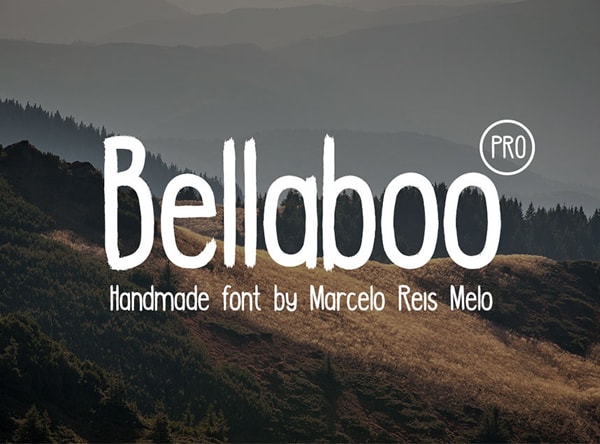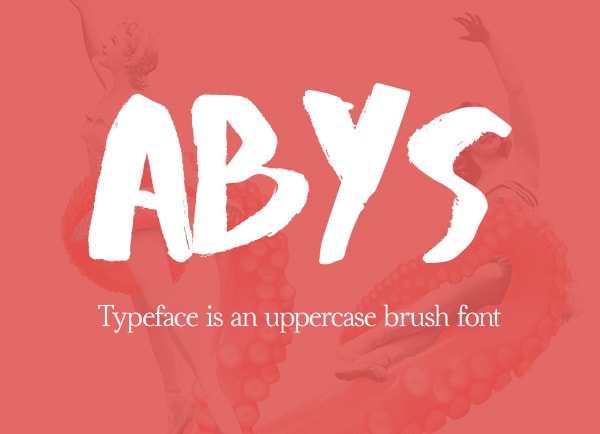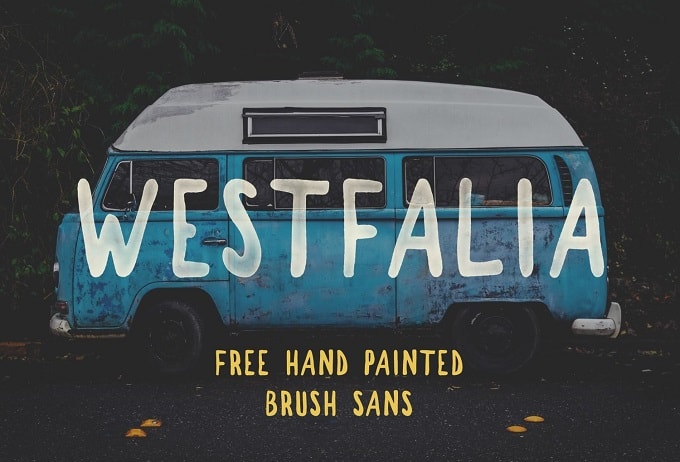
Pada dasarnya jenis-jenis font dibagi menjadi 5 bagian yaitu: Roman, San Serif, Egyptian, script dan Miscellaneous. Singkatnya jenis font ini dibedakan atas dasar bentuk dan penggunaan dari font tersebut.
Roman dikenal memiliki ciri terdapat sirip/kaki/serif berbentuk lancip pada ujungnya, Egyptian memiliki ciri yang sama dengan Roman hanya saja bentuk sirip/kaki/serif dari Egyptian persegi seperti papan dengan ketebalan yang sama dan kesan yang ditimbulkan adalah kokoh, kuat, kekar serta stabil. Kemudian ciri utama dari script font adalah menyerupai goresan tangan yang dikerjakan dengan pena, kuas atau pensil tajam dan biasanya miring ke kanan, kesan yang ditimbulkan dari font ini adalah sifat pribadi yang akrab.
Namun ada jenis font lain yang tidak termasuk dalam 5 jenis font diatas yaitu adalah Brush font dan inilah yang menjadi fokus utama pada artikel ini. Seperti namanya hal paling mencolok dan khas dari jenis font ini adalah bentuk font yang seolah-olah dibuat dengan gaya sapuan kuas dan ukuran huruf yang tebal. Jenis Brush Font ini cocok digunakan untuk desain logo, Header Poster atau website.
Abys – Free Brush Font
Avene – Free Brush Font
Bellaboo PRO – Free Brush Font
Besom – Free Brush Font
Black Animal – Free Brush Font
Bleakerst – Free Brush Font
Broken Wings – Free Brush Font
Bruss – Free Brush Font
BRUX – Free Brush Font
Debby – Free Brush Font
Fancy – Free Brush Font
Fibre (Vintage) – Free Brush Font
Flow – Free Brush Font
FOXHOLE – Free Brush Font
Frutilla – Free Brush Font
Gladysta – Free Brush Font
Happy Camper – Free Brush Font
I Need Coffee – Free Brush Font
Israt – Free Brush Font
King Basil – Free Brush Font
Leafy – Free Brush Font
Lemon Tuesday– Free Brush Font
Marjei – Free Brush Font
Mightype – Free Brush Font
Morsal – Free Brush Font
Naira – Free Brush Font
Neaments – Free Brush Font
Olivia – Free Brush Font
Parabola – Free Brush Font
PLUME – Free Brush Font
Rainwood – Free Brush Font
Rowo – Free Brush Font
Salted Mocha – Free Brush Font
SickBoy – Free Brush Font
Sloppy – Free Brush Font
Syabab – Free Brush Font
Tipper – Free Brush Font
The Woodlands Typeface
Adalah modern caligraphy font yang diciptakan untuk memberikan alterative font gratis yang tidak kalah bagus dengan font premium untuk membuat desain tipografi terlihat lebih menarik dan elegan, gratis untuk personal ataupun komersial.
Tombow – Free Brush Font
Westfalia – Free Brush Font
Wild Youth – Free Brush Font